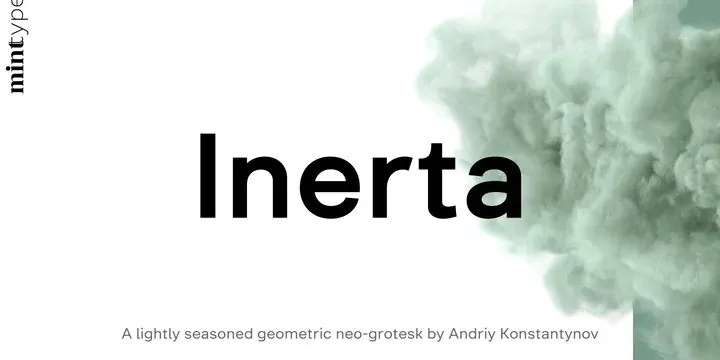
A Inerta Font é uma escolha ideal para projetos digitais contemporâneos, especialmente para aplicativos de interface do usuário (UI) e interação com o usuário (UX). Desenvolvida por designers de um concurso online na 99designs, esta fonte sem serif oferece uma atmosfera elegante, limpa e sofisticada. Sua simplicidade permite que seja usada em aplicações digitais modernas, como websites e aplicativos móveis, mantendo-se levemente discreta para não desviar a atenção do design. O equilíbrio entre simplicidade e estética chama a atenção de forma suave sem prejudicar a legibilidade, garantindo que os detalhes importantes permanecam visíveis, mesmo em fontes muito pequenas. A Inerta Font também é versátil o suficiente para atender aos mais variados requisitos linguísticos. Com uma ampla gama de 950 caracteres, ela suporta vários idiomas e oferece múltiplas opções de tipografia para adaptar ao seu próprio estilo e estilo visual, tornando-se perfeita para projetos internacionais ou com diversos destinatários linguísticos. Por fim, é uma escolha atraente para designers que buscam um equilíbrio entre simplicidade moderna e elegância sofisticada em seus projetos digitais.